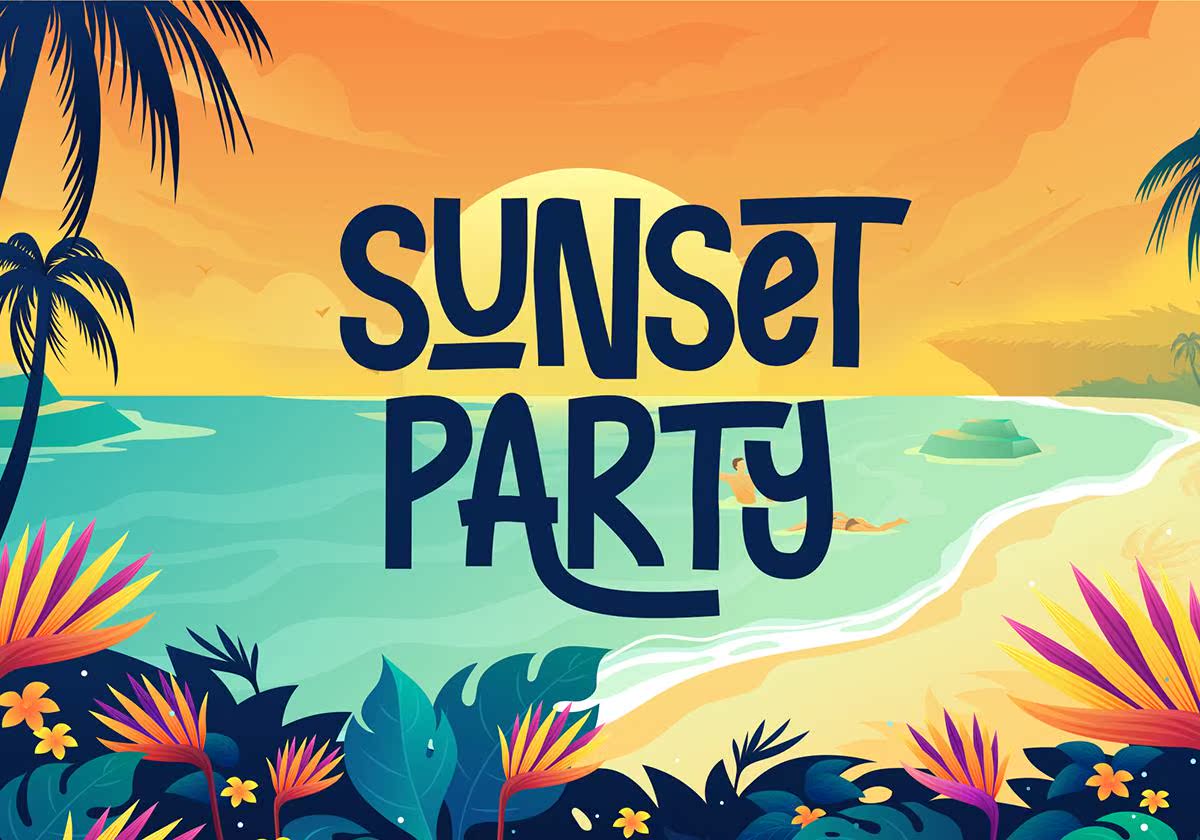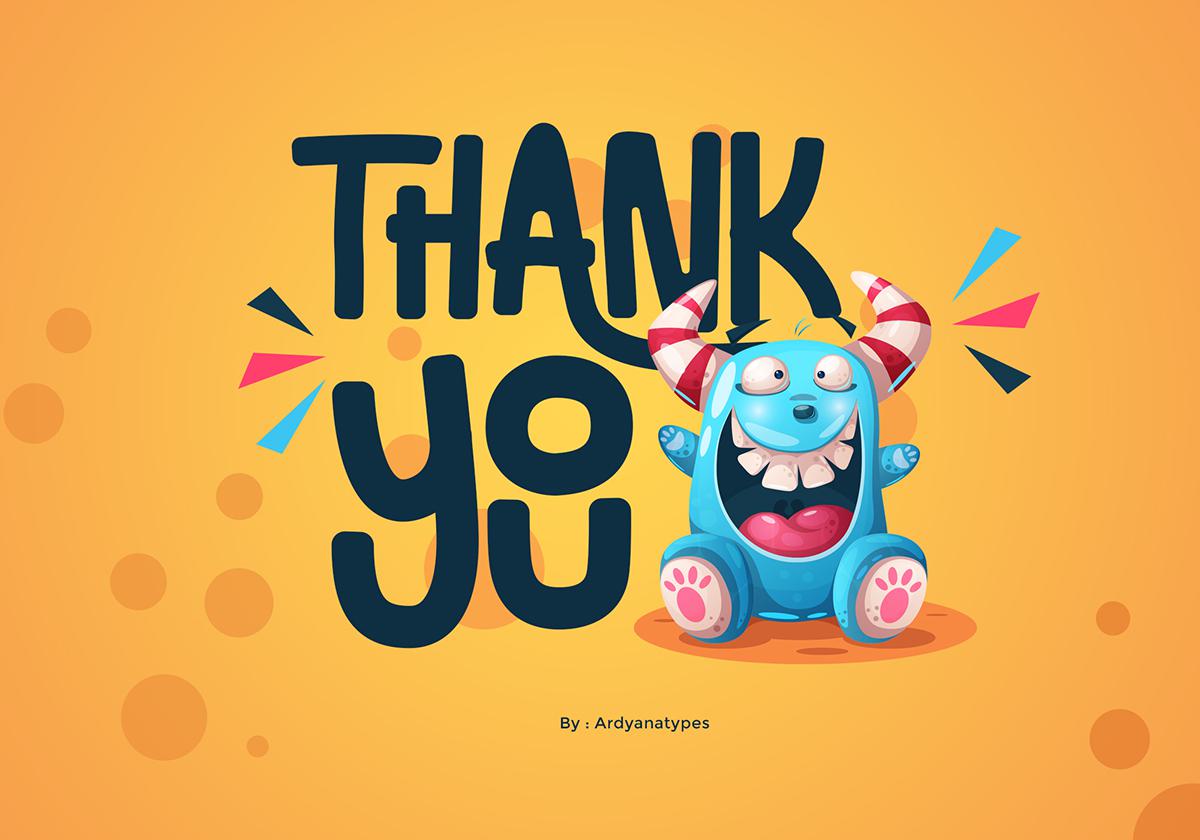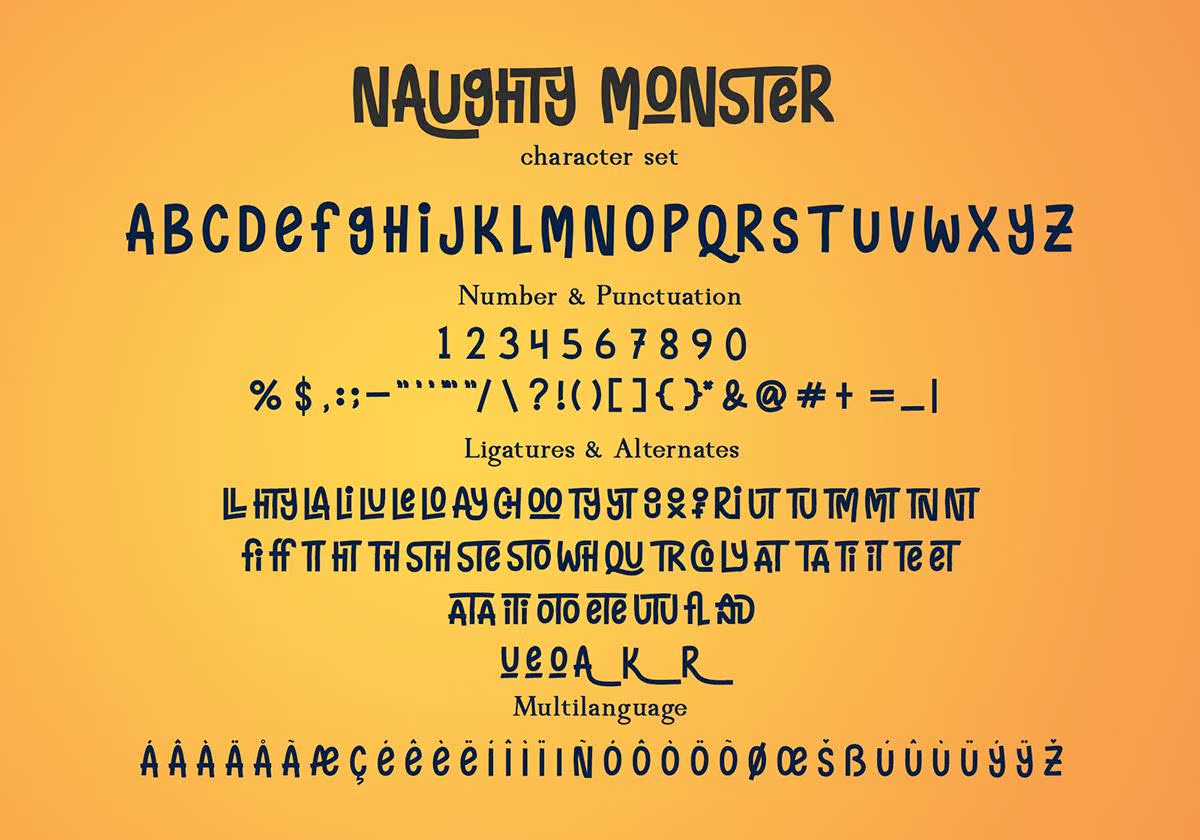
FreeNoutyMonsterDisplayFont是一款非常适合您的作品的Font。它与一种能让您的作品看起来既有趣又甜美的混合风格相结合。该Font还具有多种语言的功能,为您的FreeFont提供TFand格式文件,您可以安装您的任何设备。它非常适合您的项目,包括包装、横幅、礼品卡、传单、提案、,还有更多。所以,个人使用许可证是可能的,但是,如果你想获得更多的好处,请确保你购买了PremiumVersion。